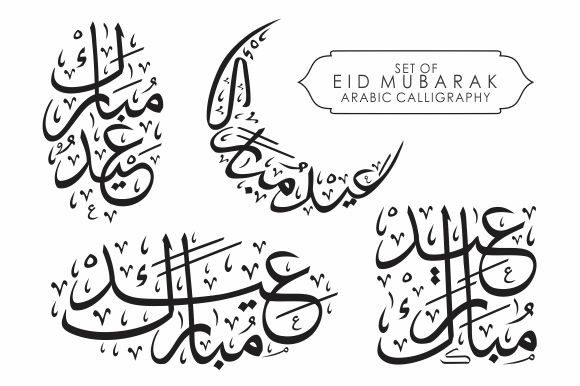
Set of Eid Mubarak Calligraphy
適切なデザイン要素を見つけるのは難しい場合がありますが、Set of Eid Mubarak Calligraphyは作品を即座に引き立てる優れたコレクションを提供します。
POD(オンデマンド印刷)製品、結婚式の招待状、またはソーシャルメディアのグラフィックを作成している場合でも、Set of Eid Mubarak Calligraphyは理想的です。